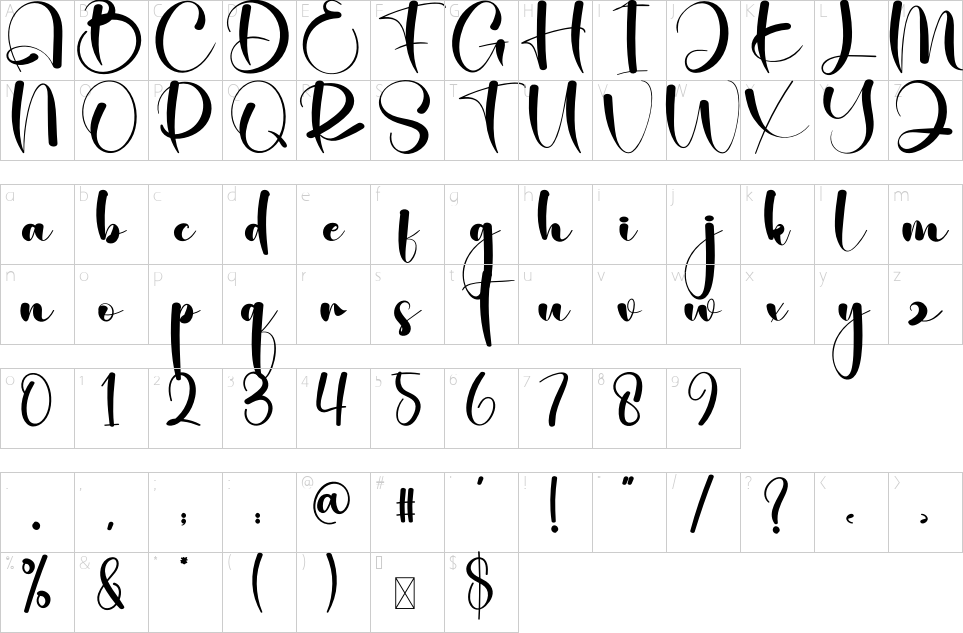
Descubra a magia do Natal com nossa Groovy Christmas Font – um design criado por scratchones que você pode usar livremente tanto no Windows quanto no Mac. Esta fonte, ideal para decorações natalinas e apresentações especiais, é uma excelente adição às suas ferramentas de design gráfico. Com apenas 157 downloads até agora, está claramente disponível e fácil de acessar. Sua elegância colorida certamente irá tornar seus projetos ainda mais atraentes durante esta época do ano. Descubra o brilho desta fonte única no Groovy Christmas Font – você não encontrará nada igual neste vasto acervo gratuito de fontes!